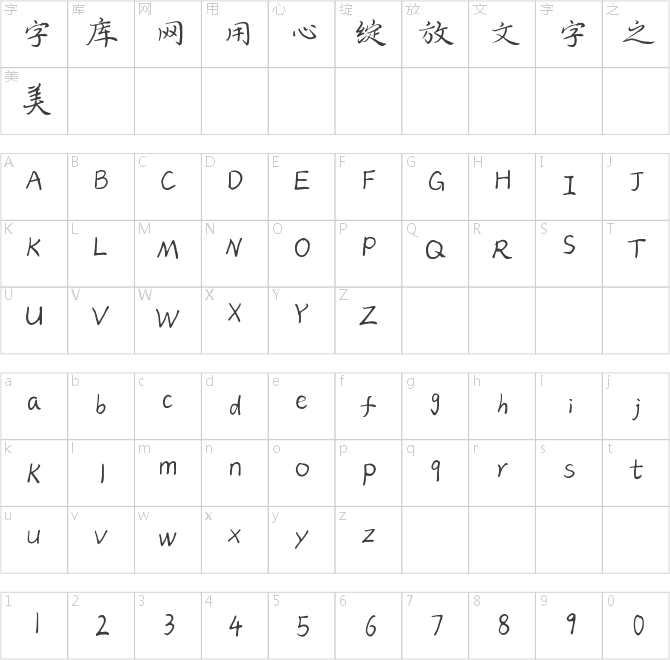
倉耳你是我唯一 詳情頁
字體名稱: 倉耳你是我唯一
倉耳你是我唯一
倉耳你是我唯一介紹
倉耳你是我唯一字體字庫是一款讓人賞心悅目、百看不厭的中文字體,適合各類廣告和產(chǎn)品包裝設(shè)計(jì)應(yīng)用,字體大小7.35MB,格式為TTF字體,上傳用戶是woslxn,作者/版權(quán)方為倉耳字庫
倉耳你是我唯一效果圖